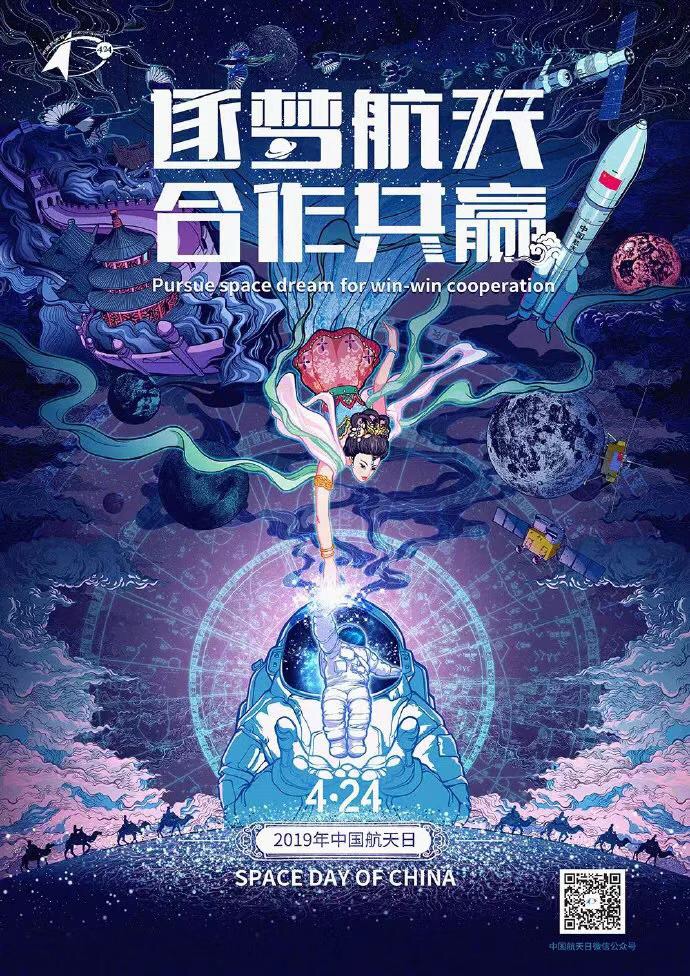
方正谭黑家族
谭新民
黑体、创意字体
方正谭黑的设计是在对综艺体进行改造的过程中形成的。这款字体的重心很高,字形的外轮廓几乎贴近字面框,字形偏扁方。笔画由粗壮的几何直线构成,局部转折处呈圆角。方正谭黑家族包含粗、细两种字重,其中细体纯用直线设计,造型更加硬朗。方正谭黑家族设计感强,个性时尚,适用于商业品牌的广告、产品包装设计和影视作品。
方正字库与设计师谭新民共同开发--方正谭黑